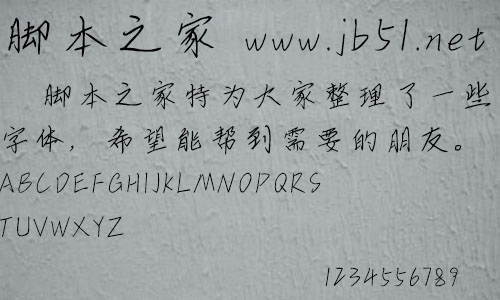
漢儀失心放手一款不錯(cuò)的藝術(shù)字體,由漢儀字庫出品,字體筆觸纖細(xì),字形灑脫,具有很好的視覺感,適合應(yīng)用于藝術(shù)設(shè)計(jì)、平面宣傳設(shè)計(jì)、網(wǎng)頁設(shè)計(jì),書法字帖等領(lǐng)域,需要的朋友可以前來本站下載。